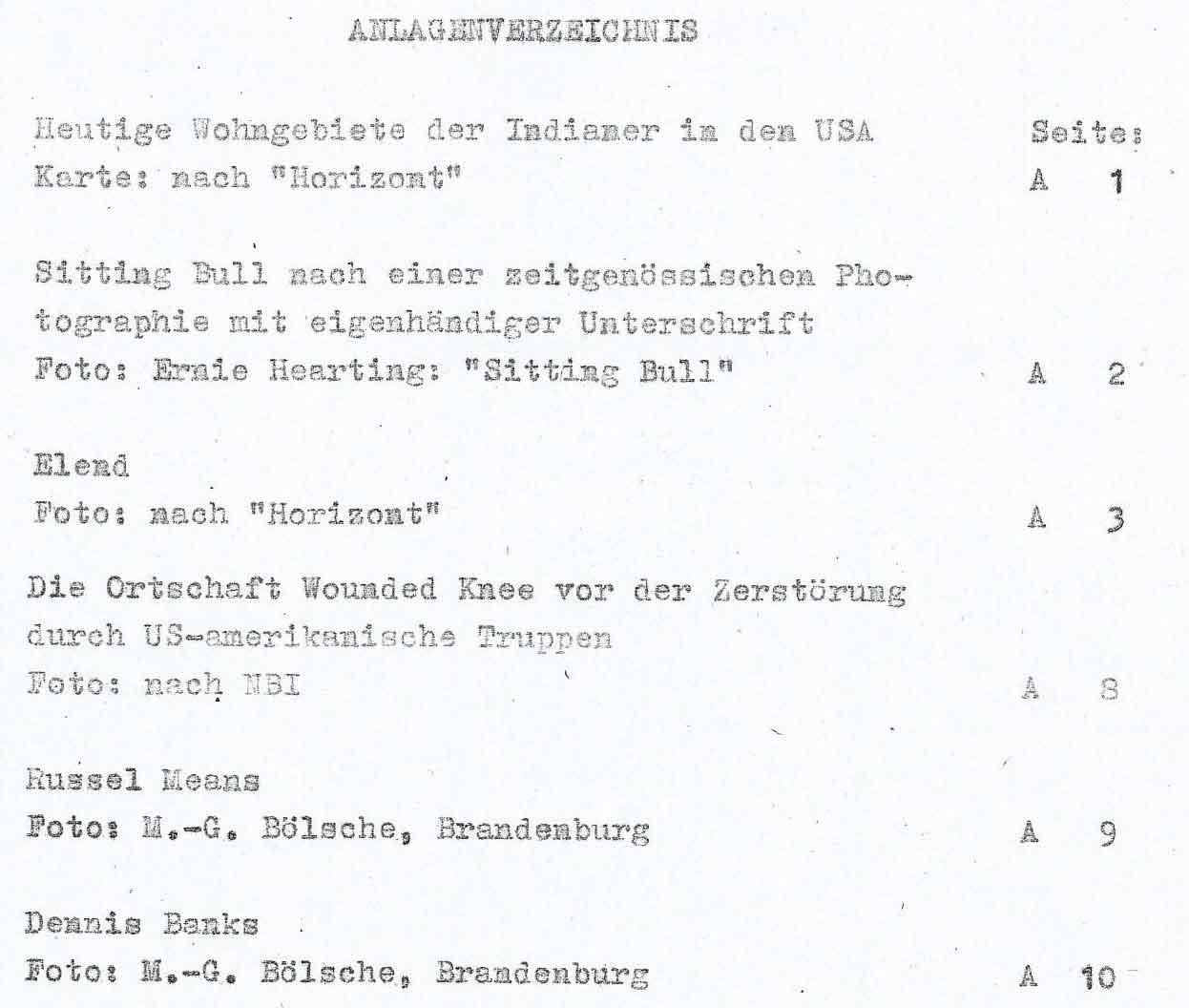
Schreibmaschine aus der DDR
ich möchte ein umfangreiches Dokument digitalisieren und dabei die Schriftart beibehalten.
Das Dokument wurde 1978 auf einer Schreibmaschine aus der DDR getippt. Möglicherweise war das ein Gerät von Optima, ist aber nicht ganz sicher. Ich würde gern entweder den Namen des verwendeten Modells oder, noch besser, den Namen der Schriftart selbst herausbekommen.
Habe es selbst mit dem Schriftbild einer "Erika" verglichen - finde, dass es dem sehr nahe kommt, dass aber auch einige Unterschiede bestehen.
Hallo Norbert, danke für den Tipp. Habe jetzt alle aufgelisteten Schriftarten verglichen.
Aber bisher haben immer noch die zwei Fonts "Erika Type" und "Erika Ormig", beide von Peter Wiegel, die größten Ähnlichkeiten mit der Schriftart in meinem Dokument.
Da ich in dieser Sache direkt angeschrieben wurde (und noch nicht dazu gekommen bin, die Mail zu beantworten) nutze ich hier die Gelegenheit zur Antwort.
Leider kann ich die genaue Schriftart auch nicht identifizieren, aber wenn meine beiden Erikas nicht reichen (wobei sich mir die Frage stellt, on man eine saubere, schreibmaschinen.ähnliche Schrift verwenden möchte, oder das rauhe Schriftbild einer etwas ungepflegten Schreibmaschine und grobem „Barock“ Farbband) gibt es noch 166 weitere Schreibmaschinen-Schrift-Digitalisierungen hier: Dafont.com
Ichg habe auch mal geschaut, ob sich die original-schriftasrt auch so digitalisieren ließe, auf dem mir zugesendeten Blatt fehlen mir dann noch mindestens Q, X, Y, p, q, w, x, ß, sowie die meisten Schreibmaschinen Satzzeichen außer . , und :
Dies vektorisiert würde dann allerdings eine etwas gröbere „Benutzte Schreibmaschine“ Schrift ergeben, die nicht so fein das Bild des Gewebes vom Farbbband wiedergibt, da dies die Schrift dann wegen der dann zu vielen Knoten zu langsam machen würde.
Generell müsste man in so einem Font dann jeden Buchstaben (zumindest die Gemeinen) mehrfach enthalten haben, die über Openbtype gewechselt werden, um ein recht „echtes“ Schreibmaschinen-Schriftbild zu produzieren.